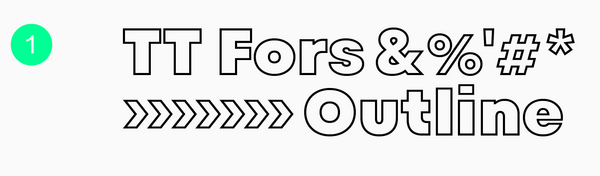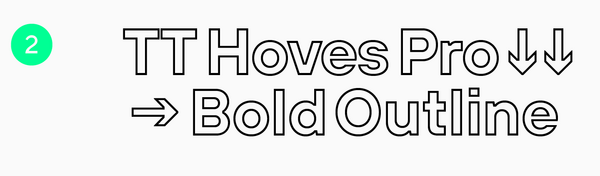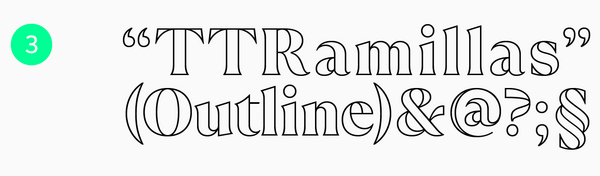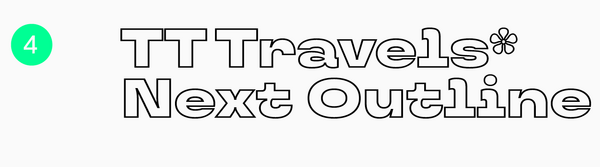
Rekomendasi Outline Font untuk Desain Grafis
Style font memiliki banyak sekali variasi, mulai dari yang bersih, rumit, memiliki serif hingga yang hanya berupa garis outline. Banyaknya variasi style font akan membantu menciptakan desain yang semakin menarik. Ketika akan memilih jenis font outline, pilih rekomendasi font yang menarik dan cocok dengan pesan yang ingin disampaikan desain.
Variasi jenis-jenis font dapat menciptakan desain grafis yang semakin menarik, beragam dan tajam. Outline dalam huruf dapat divariasikan dengan menarik agar font tampak beda dari yang lain. Namun penggunaan jenis font outline ini tidak cocok untuk semua jenis desain, ketika akan menggunakan jenis font ini perhatikan kebutuhan desain.
ALASAN MEMILIH JENIS FONT OUTLINE FONT
Ada banyak jenis variasi outline yang bisa menciptakan tampilan menarik, style outline font biasanya dipengaruhi gaya huruf aslinya. Outline untuk jenis font dengan ujung tajam akan memiliki outline yang tajam, sama halnya dengan ujung huruf yang bulat akan memiliki tampilan outline yang bulat. Beberapa alasan memilih jenis font ini karena:
Untuk Menarik Perhatian
Meski tanpa isi dan hanya berupa garis outline penggunaan jenis font dapat menarik perhatian karena tampil beda. Jika pada umumnya font memiliki warna penuh, font ini hanya memiliki garis kontur yang tipis. Terkadang variasi ketebalan garis akan divariasikan agar lebih menarik sehingga teks lebih menarik perhatian audiens.
Jenis font ini bisa digunakan untuk menarik perhatian pada desain grafis yang sederhana dan minimalis. Desain grafis yang ingin menggunakan style font ini untuk menarik perhatian, gunakan pada jenis desain yang memiliki latar belakang bersih. Font ini mungkin akan kurang terlihat pada desain yang kompleks dengan latar sibuk.
Menciptakan Hirarki Visual
Dalam desain grafis style font yang hanya berupa garis kontur ini juga bisa membantu menciptakan hirarki visual. Kombinasikan dengan jenis font yang memiliki warna penuh sehingga menciptakan hirarki. Perbedaan fill font dengan outline font akan membantu audiens fokus pada teks penting.
Desain grafis dengan tampilan font outline ini seringkali memiliki kesan modern, formal dan kaku. Untuk itu kombinasi dengan fill font yang sama tetapi tetap memiliki style berbeda agar tercipta perbedaan. Kombinasi kedua font tersebut lebih efektif menunjukkan adanya perbedaan tingkat kepentingan informasi.
Mudah Terbaca dalam Ukuran Besar
Agar mudah terbaca seringkali jenis font ini akan digunakan dalam ukuran yang besar. Penggunaan style font ini tidak akan cocok jika digunakan untuk paragraf karena akan sulit untuk dibaca. Jenis font ini akan lebih cocok untuk digunakan sebagai judul karena akan berukuran besar dan mudah dibaca.
Menciptakan Tampilan Unik
Font ini juga akan menciptakan desain logo yang unik, karena style font berbeda dengan font logo pada umumnya. Pilih jenis font outline yang cocok untuk merepresentasikan brand. Biasanya logo dengan font ini cocok untuk bisnis terkait teknologi, logo perusahaan atau logo cafe.
Tidak hanya pada logo, font ini juga menciptakan tampilan menarik untuk desain poster. Desain poster bertema futuristik dan minimalis akan cocok dan tampil dengan font yang hanya memiliki garis luar. Untuk digunakan pada desain website dan desain aplikasi sebaiknya digunakan untuk headline.
Menciptakan Kontras
Font dengan style unik akan tampil beda dan efektif menciptakan kontras jika disanding dengan dengan jenis fill font. Manfaatkan jenis font ini untuk menciptakan desain dengan visual menarik. Style font ni efektif menciptakan kontras jika disandingkan dengan font lainnya. Font akan lebih efektif menciptakan kontras yang jelas antar teks terutama untuk judul dan sub judul.
REKOMENDASI OUTLINE FONT
Ketika memilih jenis font untuk desain grafis, pilih rekomendasi font outline yang cocok dengan jenis desain dan gaya desain yang digunakan. Ada banyak variasi outline yang menciptakan mood berbeda sehingga perlu dipilih dengan bijak. Berikut beberapa rekomendasi font outline yang menarik:
TT Fors
Seringkali jenis font yang menggunakan style outline akan memiliki tampilan bersih seperti font sans serif. Jenis font TT Fors ini juga memiliki tampilan huruf bersih ruang huruf yang luas sehingga terlihat font tebal dan mudah terbaca. Proporsi huruf dalam font ini terlihat memiliki karakter yang netral dan sedikit pendek.
Bentuk huruf dalam font ini seperti bentuk geometris kotak, lingkaran dan segitiga, yang mana memberikan kesan modern. Font yang bersih dan mudah dibaca membuatnya mudah beradaptasi dan bisa digunakan secara luas. Penggunaan font ini dapat menciptakan tampilan font yang menarik perhatian dan cocok untuk desain minimalis.
Ketika ingin memilih style font yang unik, pertimbangakn untuk memilih jenis font yang hanya memiliki outline sementara ruang huruf kosong. Font ini akan tampil unik dan berbeda, penggunaan akan efektif menarik perhatian. Penggunaan jenis font ini banyak dipilih untuk desain brand fashion, desain minimalis dan desain bertema futuristik. PIlih style font yang paling cocok dengan gaya visual dan citra yang ingin dibangun merek.